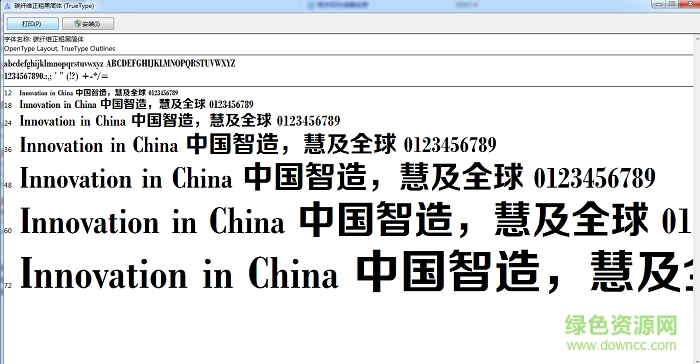
碳纖維正粗黑簡體是一款碳纖維字體,這款字體實在黑體字體的基礎(chǔ)上設(shè)計而來的,在保留黑體特點的同時又做了一些創(chuàng)新,更加時尚和實用,需要的朋友快來綠色資源網(wǎng)下載吧!
該字體看起來粗壯、大氣,可以適用于名片設(shè)計、平面設(shè)計、廣告設(shè)計、報紙雜志、企業(yè)LOGO、商標(biāo)注冊、電視臺廣告等領(lǐng)域!
黑體,是中文一類字體的名稱,與白體相反,特點是沒有襯線裝飾,筆劃粗壯有力,撇捺等筆畫不尖,使人易于閱讀,由于其醒目的特點,常用于標(biāo)題,導(dǎo)語,標(biāo)志等等。